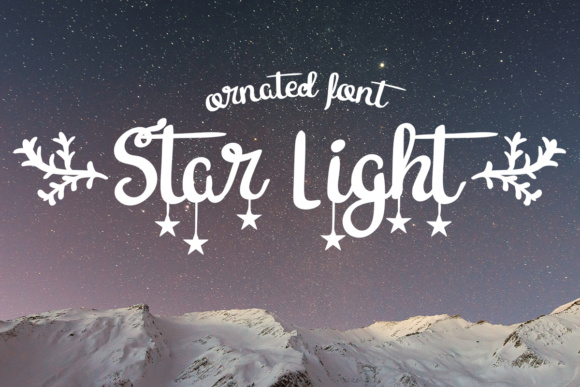
Star Light
Conçu avec précision, Star Light offre des vecteurs nets, une typographie fluide et une licence commerciale pour une tranquillité d'esprit.